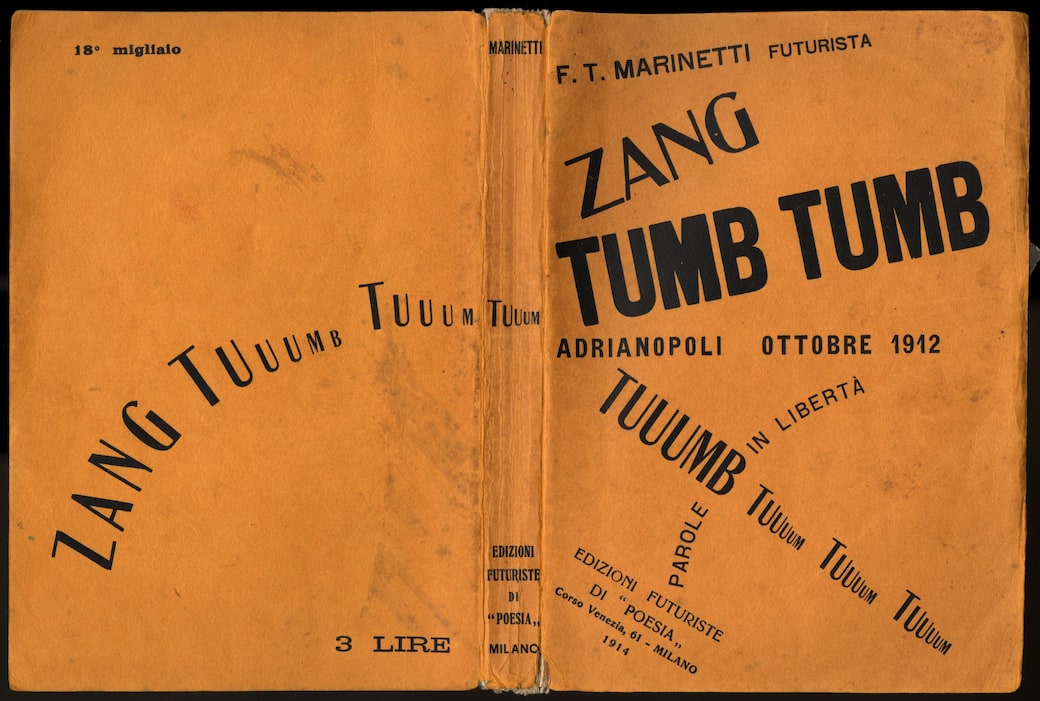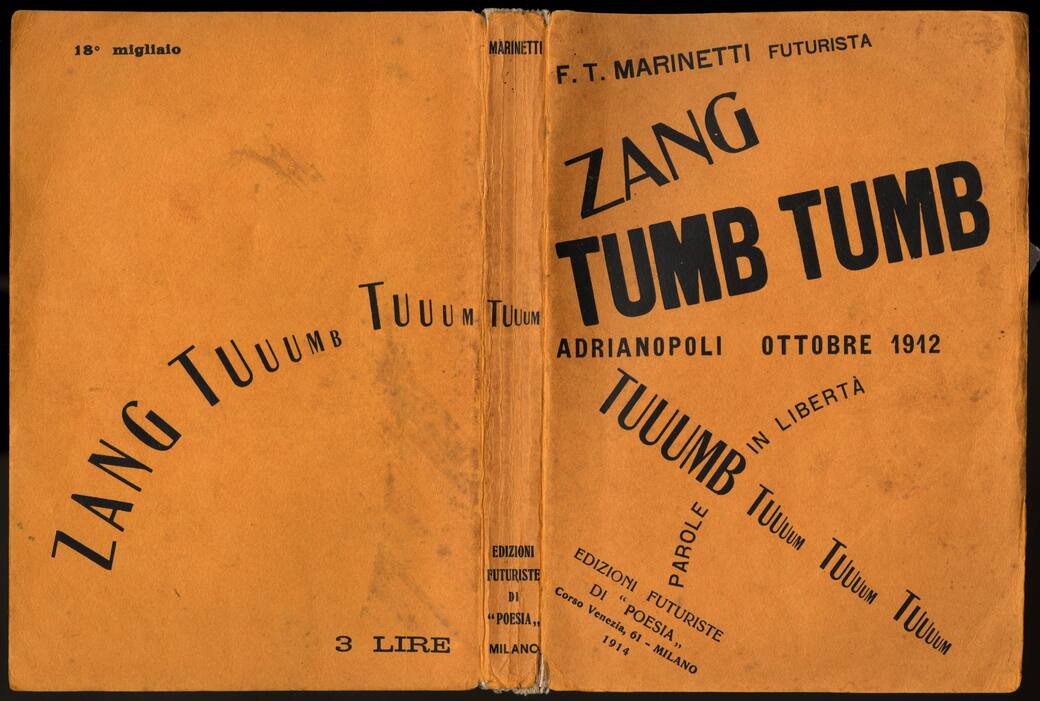
Tipografia creativa alla Casa d'Arte Futurista Depero
Qual è l'eredità delle innovazioni espresse dal movimento futurista nella grafica e nella relazione tra parola e immagine? A partire dalle sperimentazioni di Marinetti e colleghi, la nuova mostra alla Casa d'Arte Futurista Depero traccia un itinerario che ripercorre tutto il XX secolo.